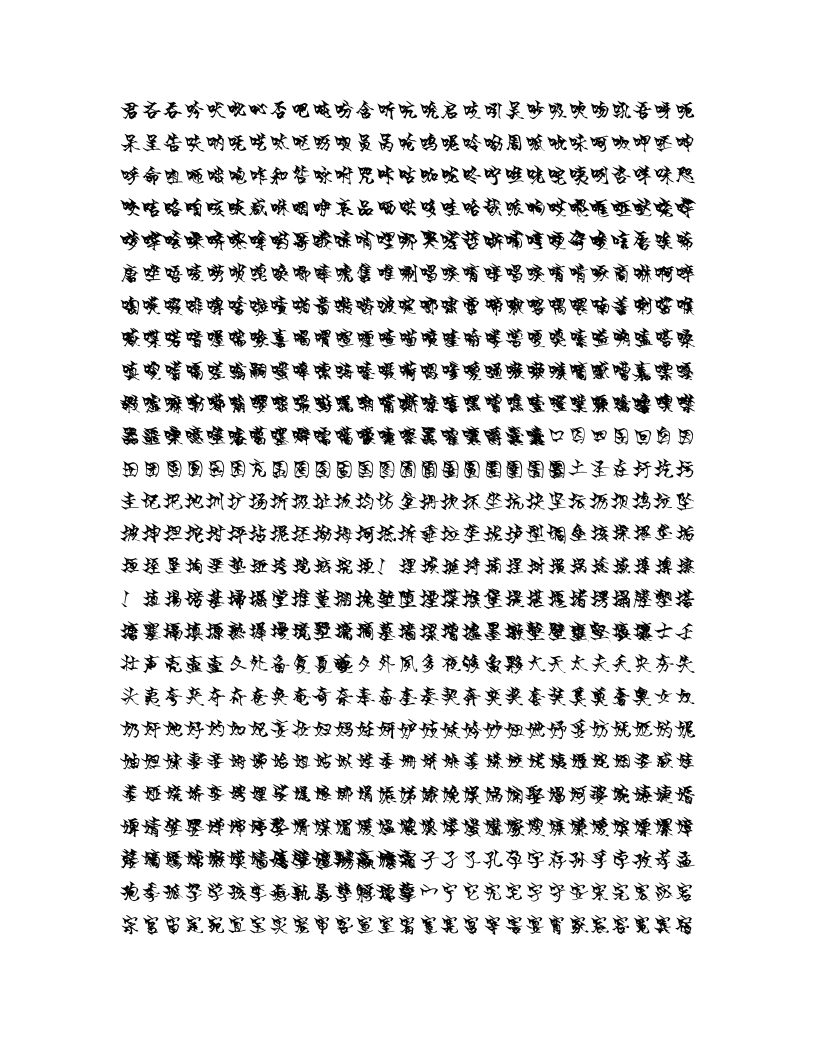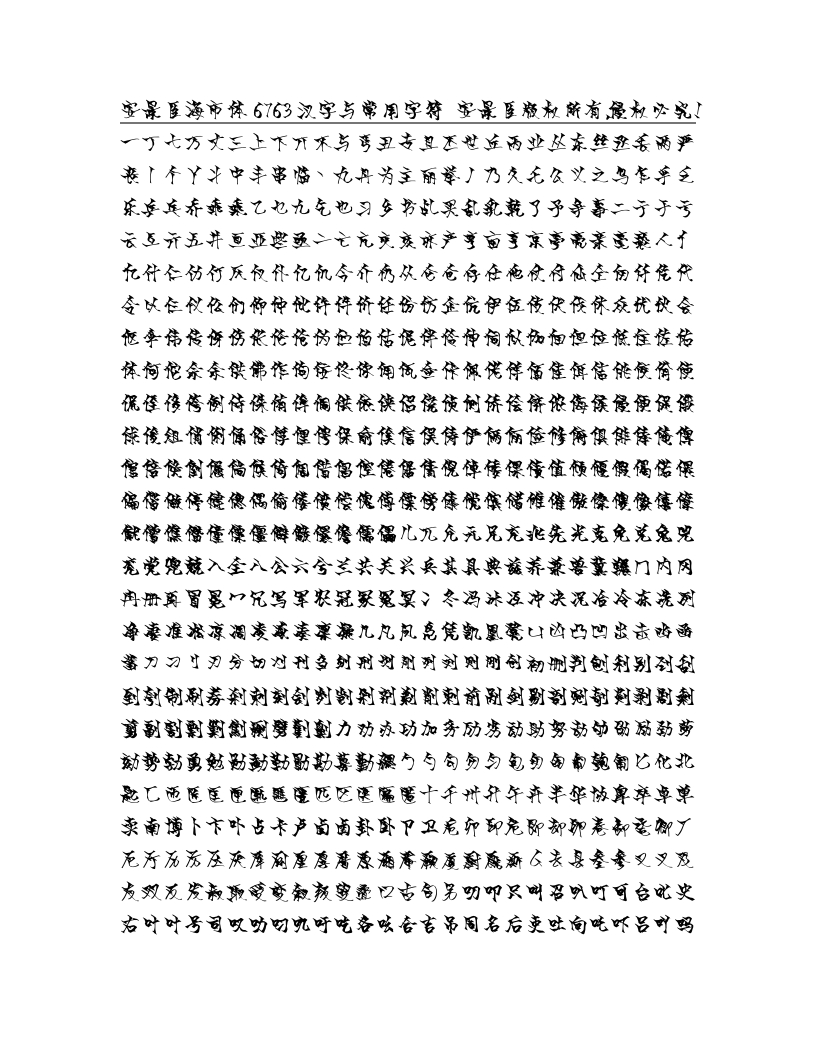
安景臣海市体(anjingchenhaishiti)
罗刹国向东两万六千里,过七冲越焦海三寸的黄泥地。
风格:手写体
语系:中文-简体
字数:GB2312(6763字)
类型:魏碑
描述:海市体是安景臣根据蒲松龄先生《聊斋志异》有关章节及刀郎老师的同名歌曲《罗刹海市》而创作的一款风格独特、雅俗共赏的字体。面向个人非商业应用免费开放,欢迎试用。商业应用请取得授权。